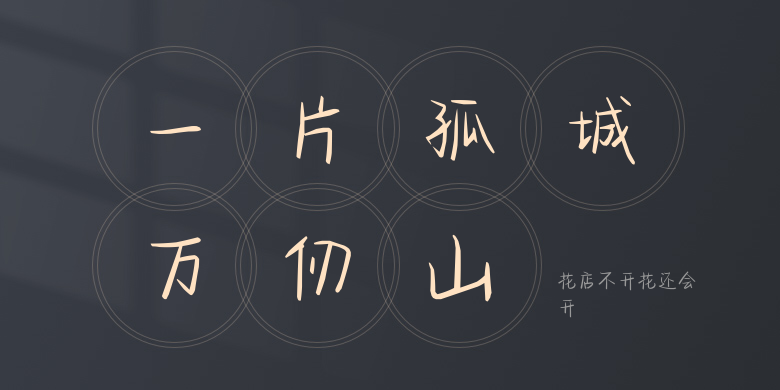
花店不开花还会开
花店不开花还会开,这款字体结构工整、笔画清晰,兼顾美观与易读性,适用于标题、正文、海报、包装、LOGO 等多种场景。字形优雅稳定,风格百搭耐看,适配日常排版与创意设计,让文字呈现更舒适、更具质感。花店不开花还会开一笔一画,皆是细节,以均衡的比例、流畅的线条打造舒适视觉体验,字形端正大气,风格简约现代。无论是商业设计、品牌宣传还是日常排版,都能轻松驾驭,让文字更有格调与力量。花店不开花还会开字体下载。